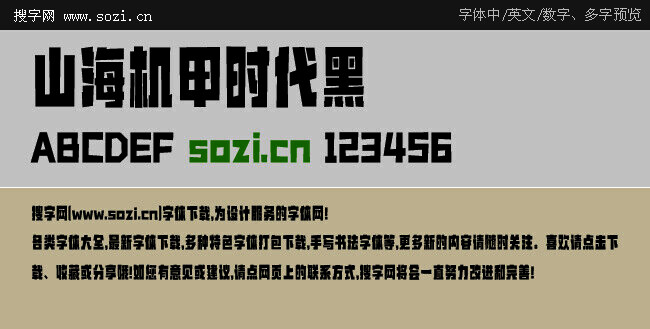
山海機(jī)甲時(shí)代黑
搜字網(wǎng)提供一款山海機(jī)甲時(shí)代黑中文藝術(shù)字體下載,山海機(jī)甲時(shí)代黑是一款綜藝標(biāo)題黑體字體,包含簡(jiǎn)體漢字6763個(gè)。該字體是一款具有強(qiáng)勁視覺(jué)沖擊力的綜藝風(fēng)格標(biāo)題字體。字形瘦高,造型硬朗,全直線的筆畫構(gòu)成棱角分明、堅(jiān)實(shí)有力。適合包裝設(shè)計(jì)、海報(bào)設(shè)計(jì)、廣告設(shè)計(jì)等應(yīng)用。